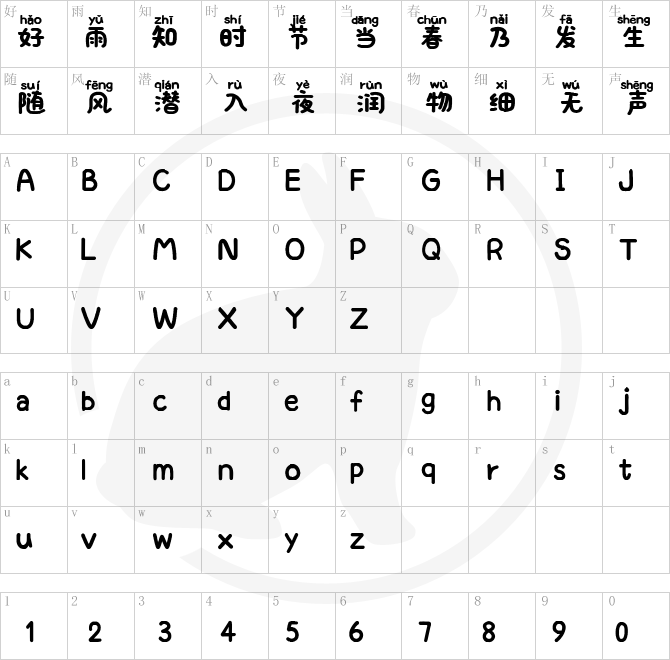
也字工厂绘本拼音体
也字工厂绘本拼音体,这款字体结构工整、笔画清晰,兼顾美观与易读性,适用于标题、正文、海报、包装、LOGO 等多种场景。字形优雅稳定,风格百搭耐看,适配日常排版与创意设计,让文字呈现更舒适、更具质感。也字工厂绘本拼音体一笔一画,皆是细节,以均衡的比例、流畅的线条打造舒适视觉体验,字形端正大气,风格简约现代。无论是商业设计、品牌宣传还是日常排版,都能轻松驾驭,让文字更有格调与力量。也字工厂绘本拼音体字体下载。